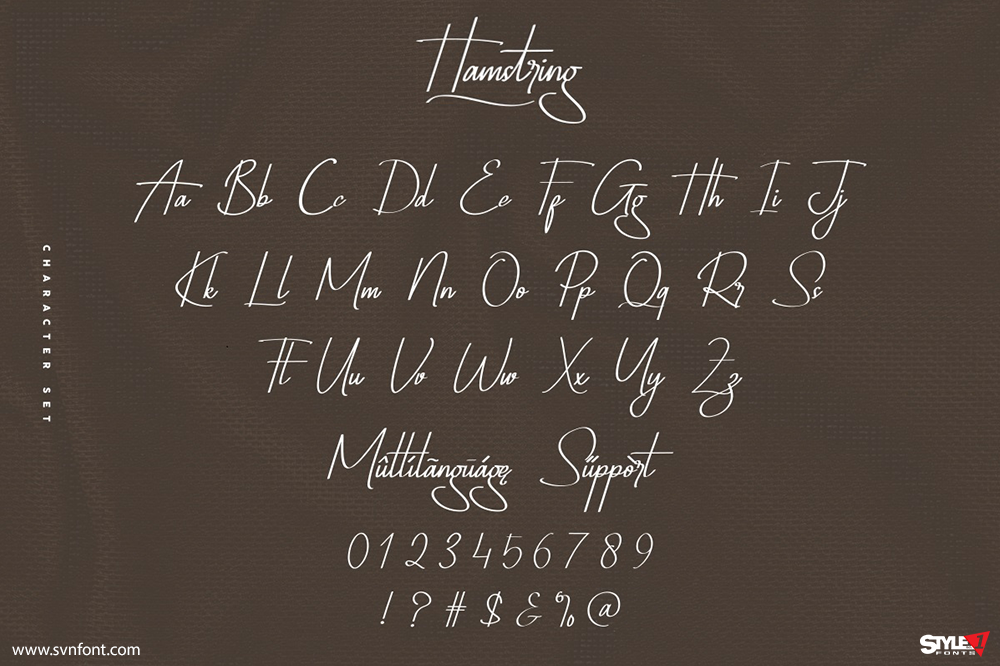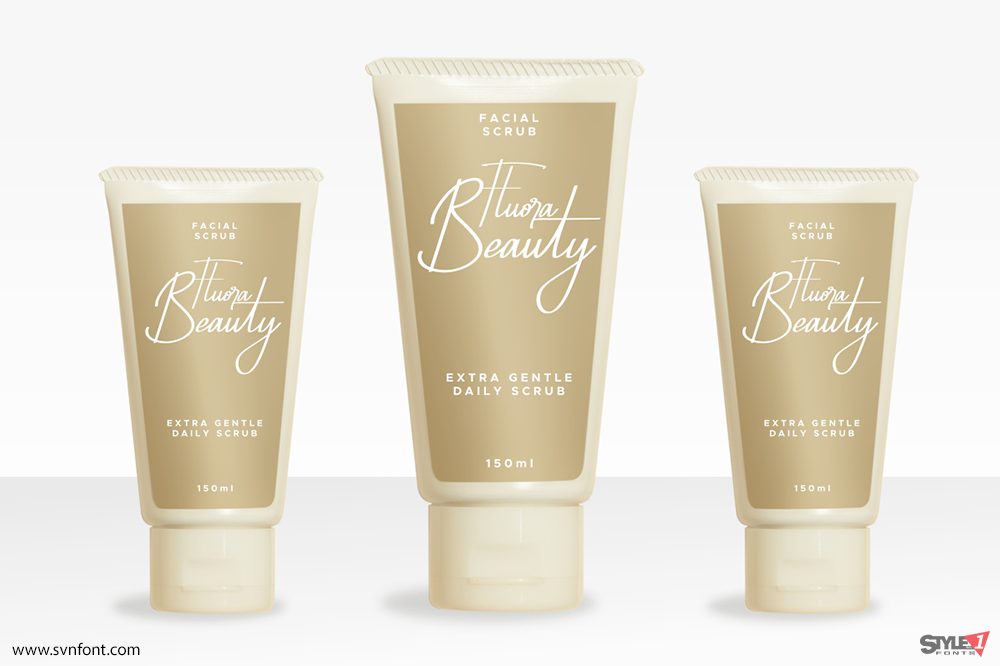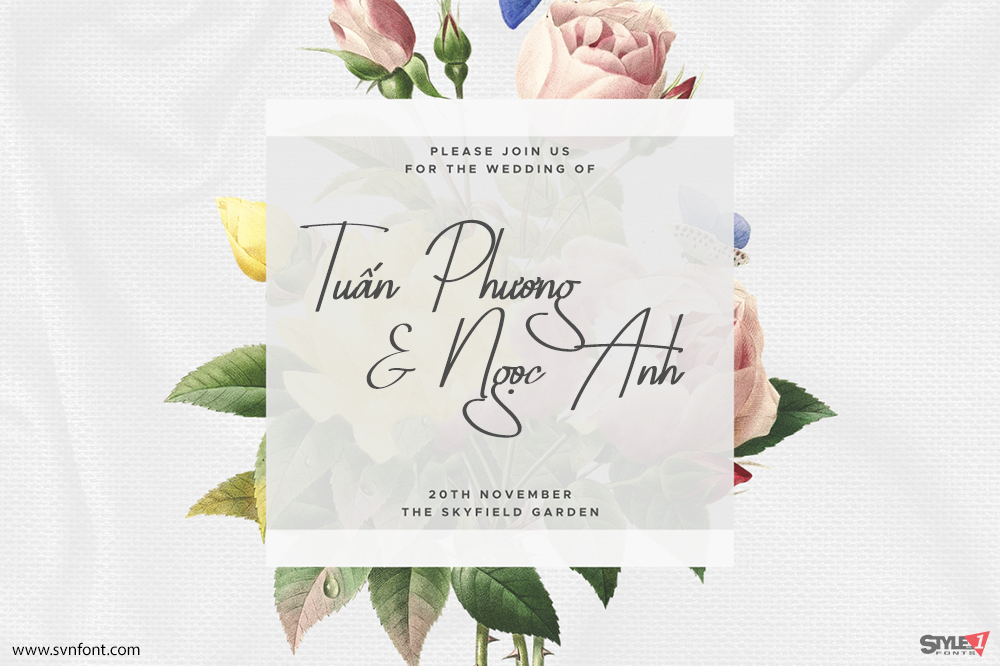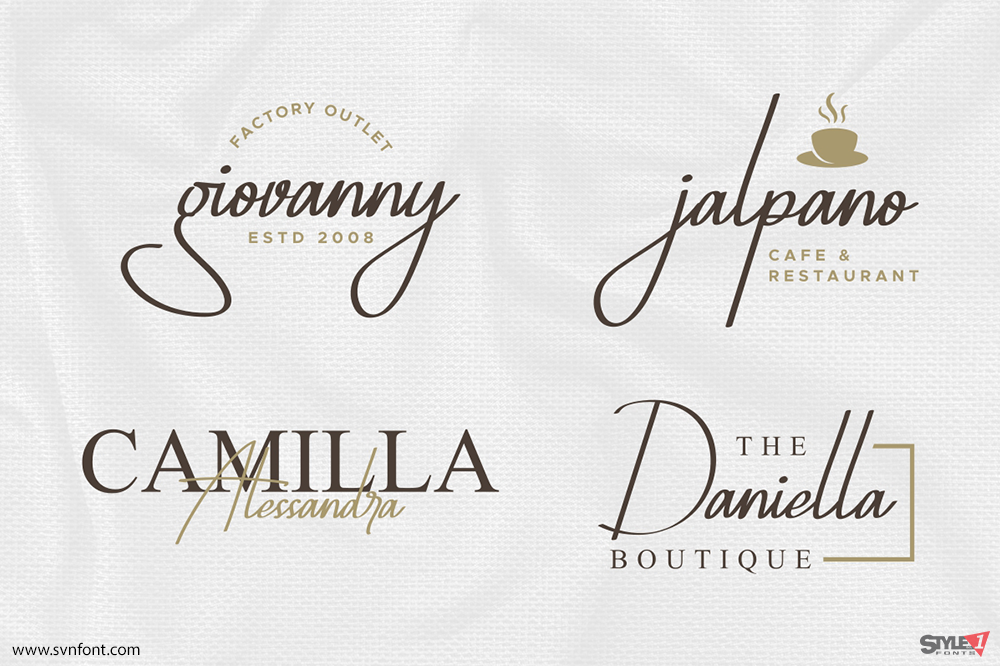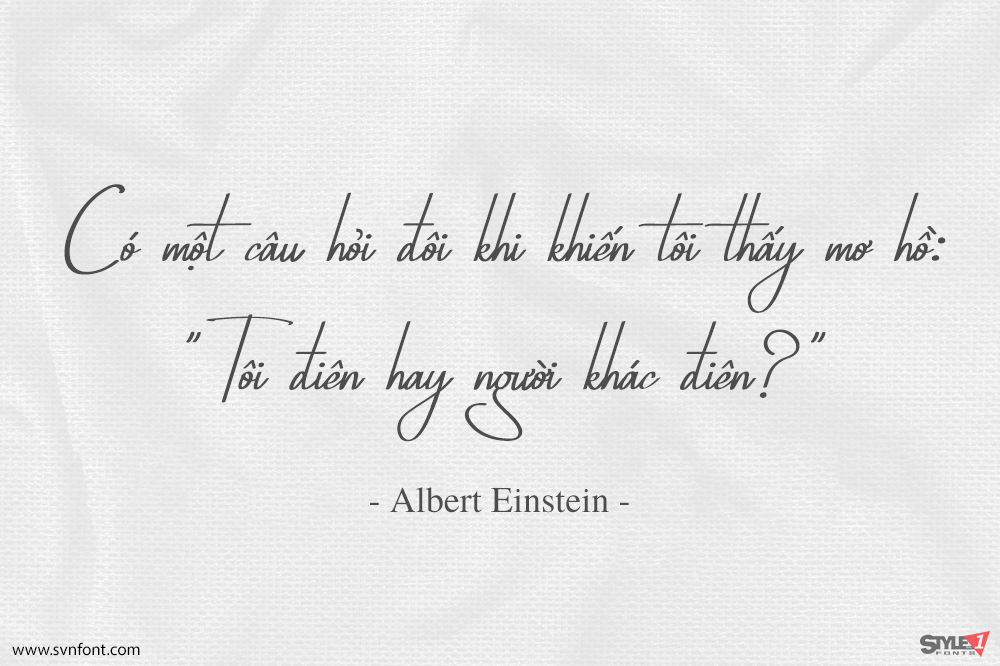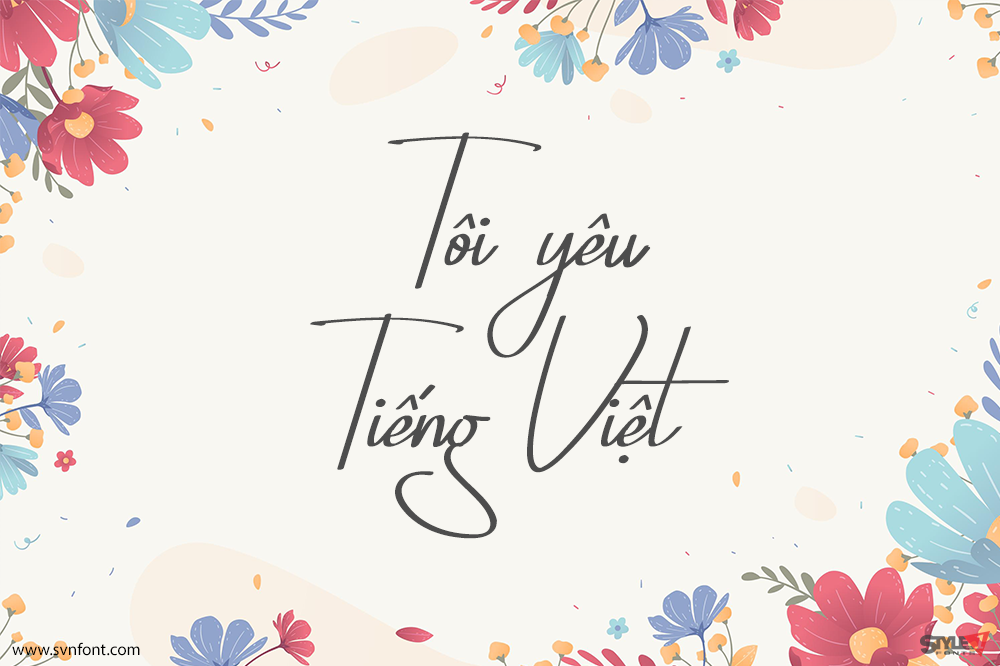
Hamstring Font là một font chữ ký viết tay mang phong cách cổ điển, được tạo ra bởi RaisProject. Font sở hữu chữ hoa, chữ thường đẹp mắt, cùng chữ số, hệ thống dấu câu đa dạng và ligature, rất phù hợp cho các thiết kế cần cảm giác tự nhiên, tinh tế và mang dấu ấn cá nhân.
Nhà thiết kế: Widiyanti & Sarah Suci P
Nhà phát hành: Raisproject